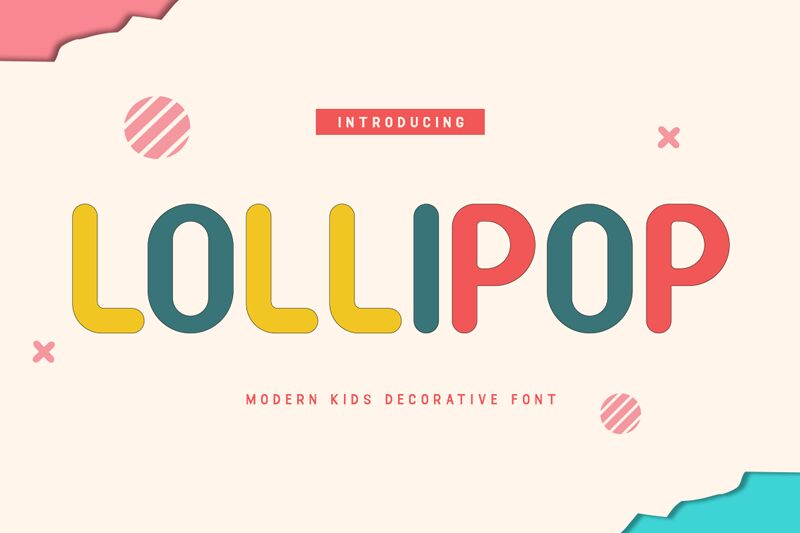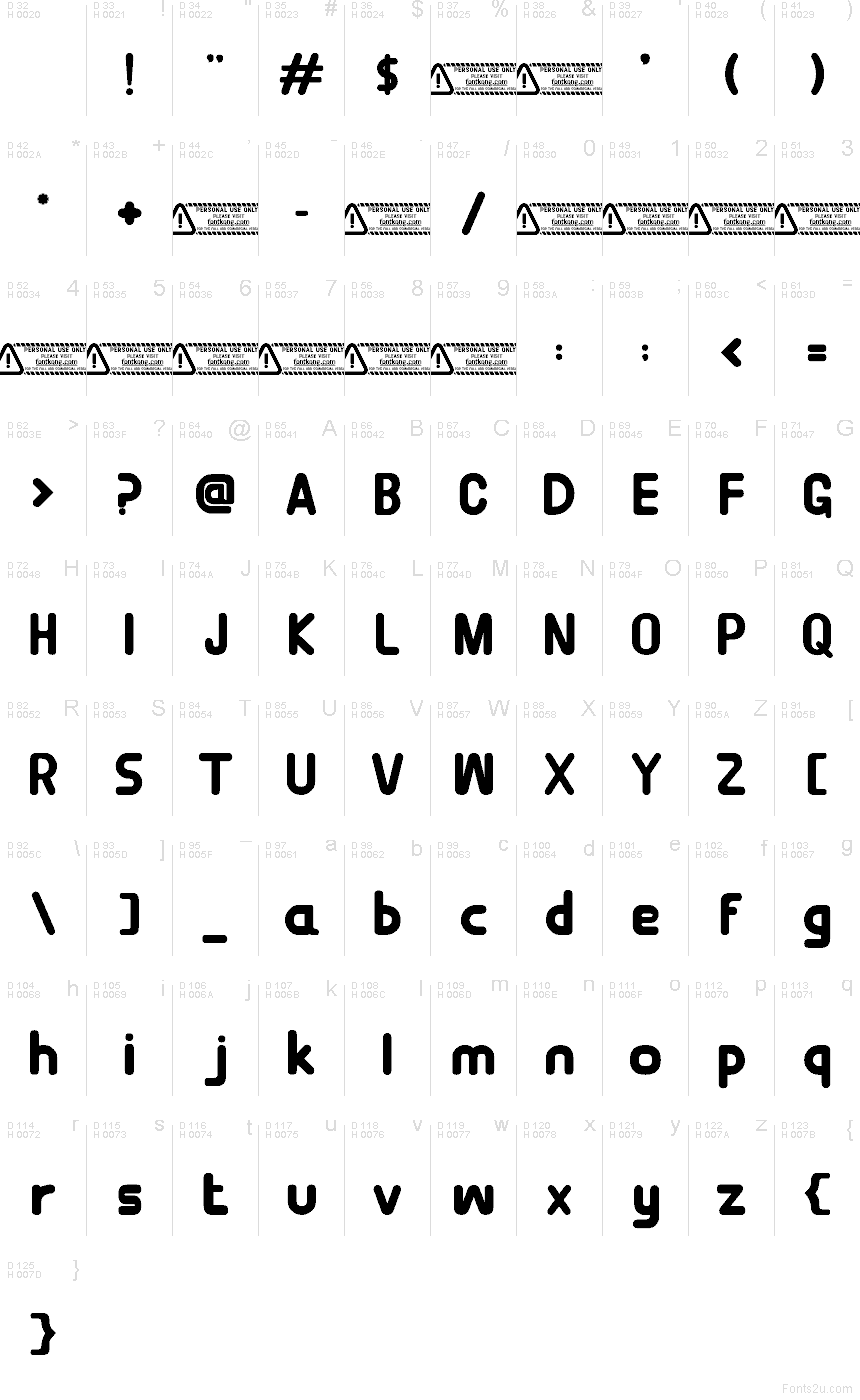
Lollipop par Kong Font est une police d'affichage arrondie gratuite, aux formes douces évoquant des bulles et aux chasses presque circulaires. Ses caractères semblent étroitement liés, avec une géométrie simple et des terminaisons arrondies qui confèrent à l'ensemble un rythme doux et compact.
Lollipop fonctionne parfaitement pour les emballages de bonbons, les logos de boulangerie, les affiches pour enfants, les designs d'autocollants et les visuels pour réseaux sociaux, car ses formes arrondies véhiculent une tonalité amicale et informelle sans fioritures excessives. Elle convient également aux titres courts, aux étiquettes de produits et aux identités de marque ludiques où une police d'affichage nette et douce permet de garder une mise en page légère et directe.